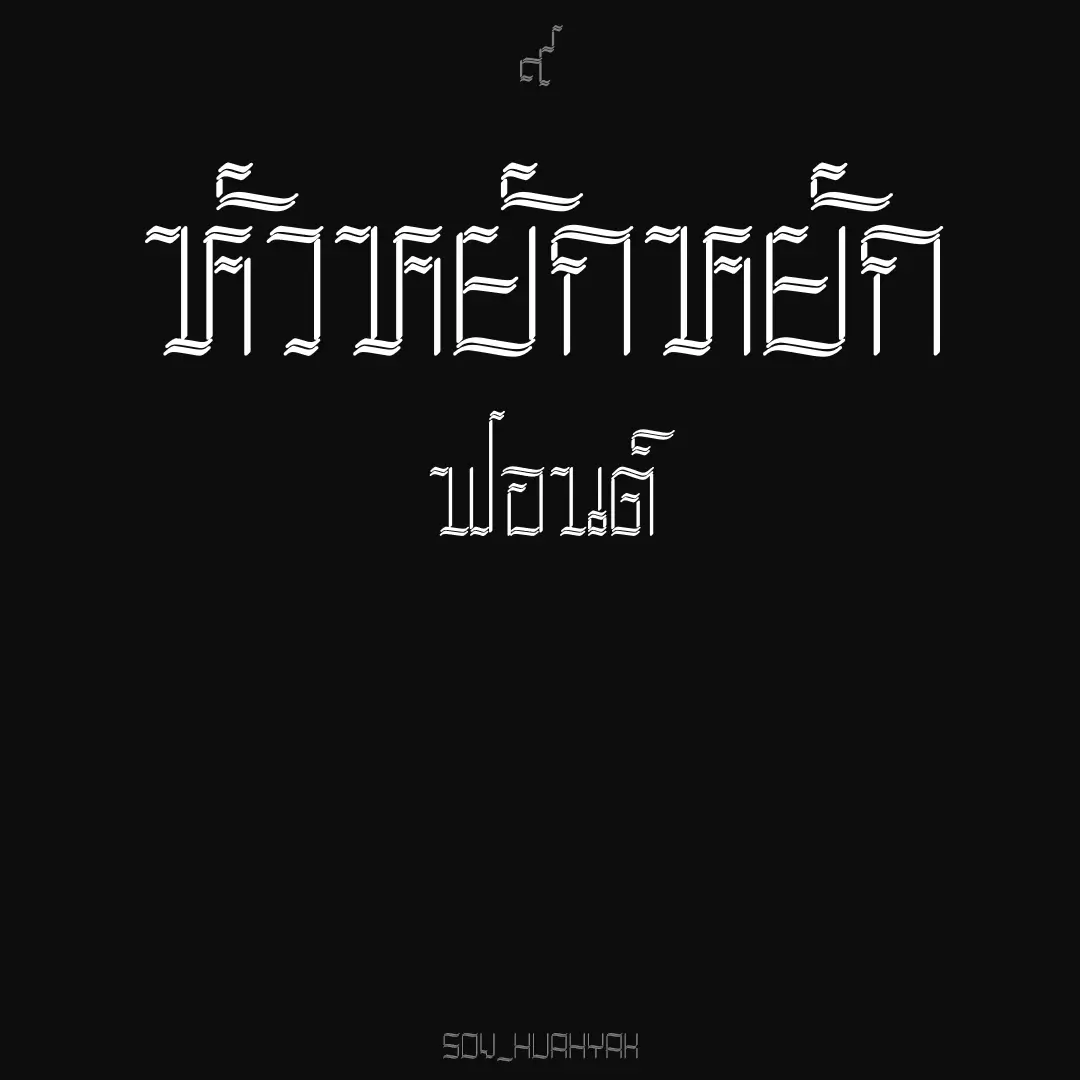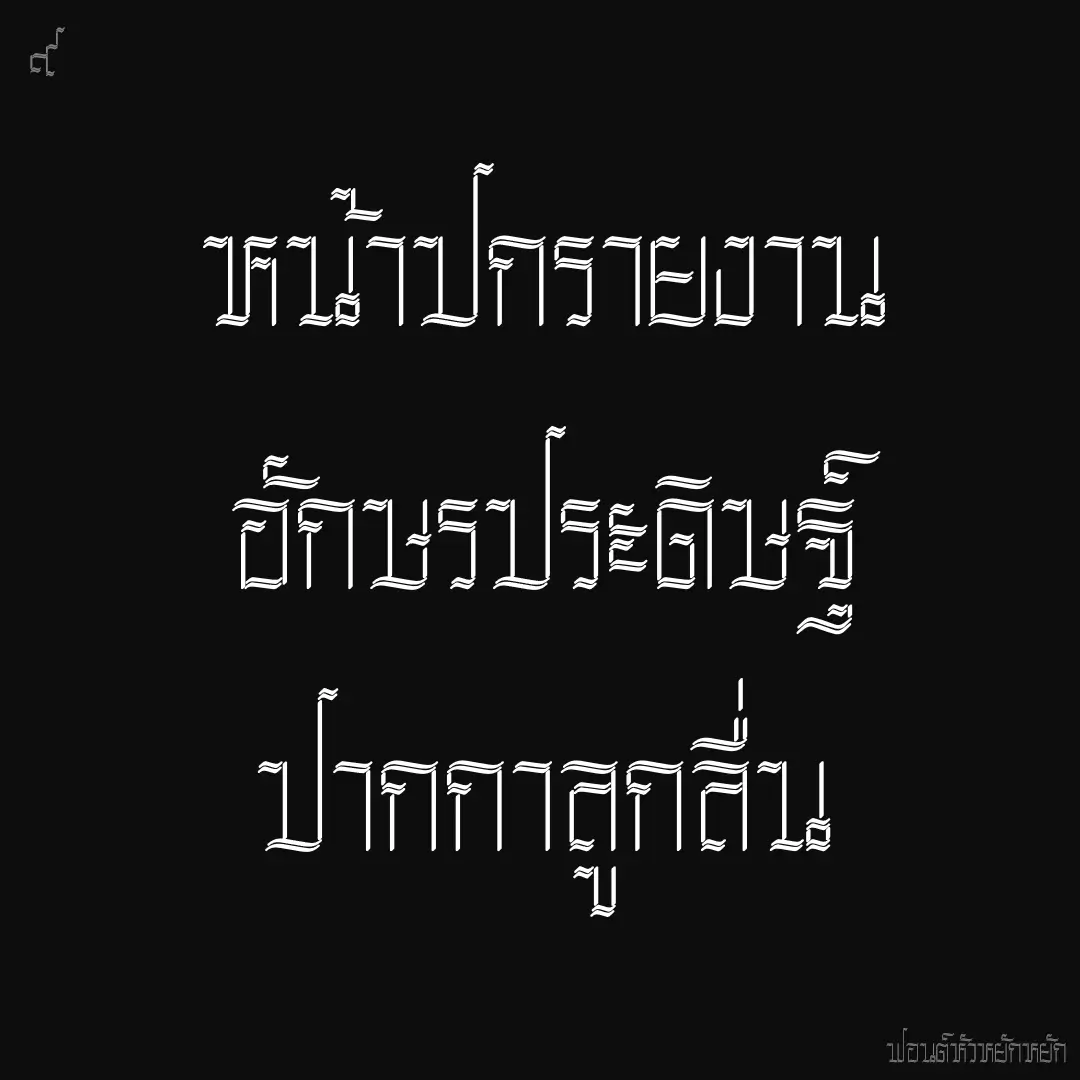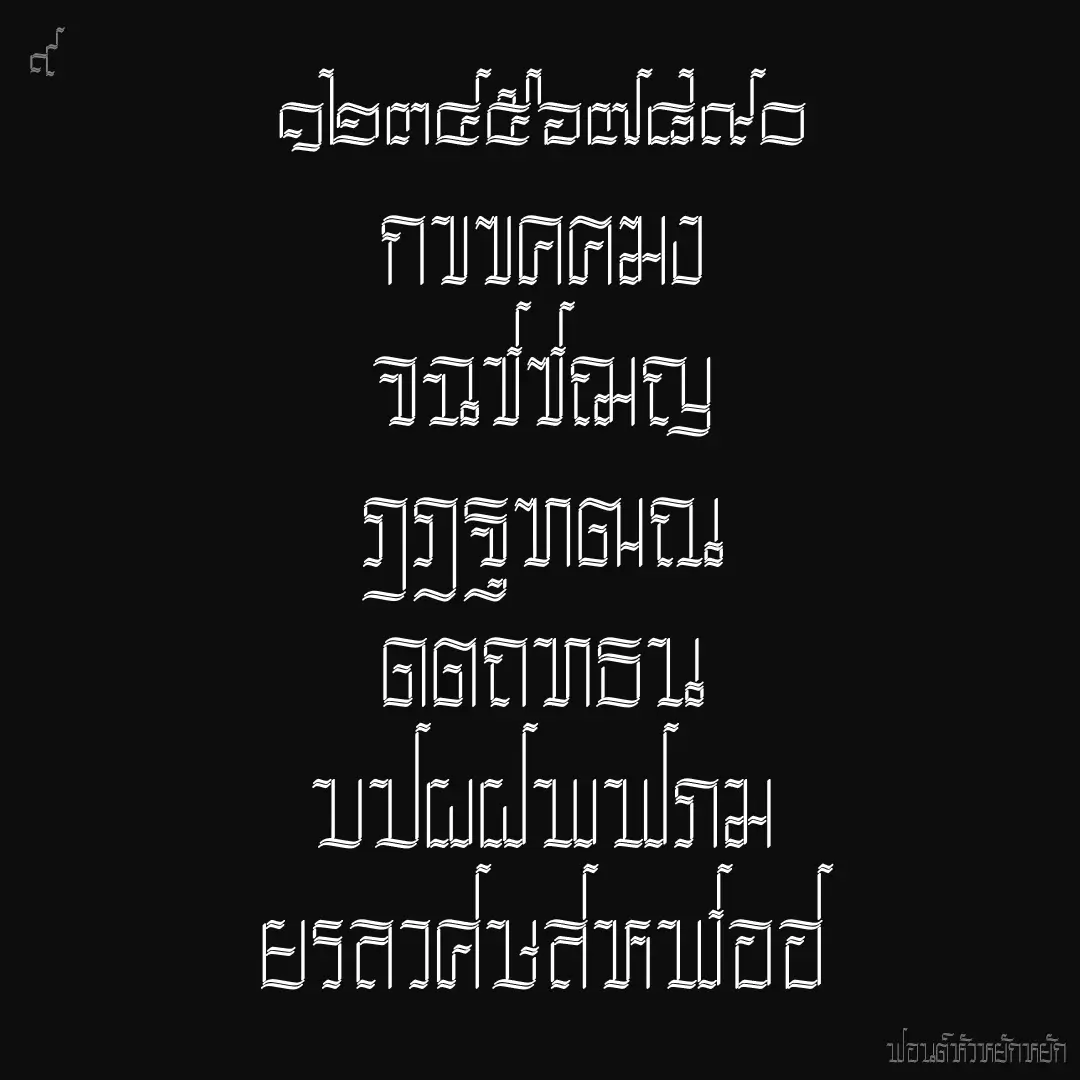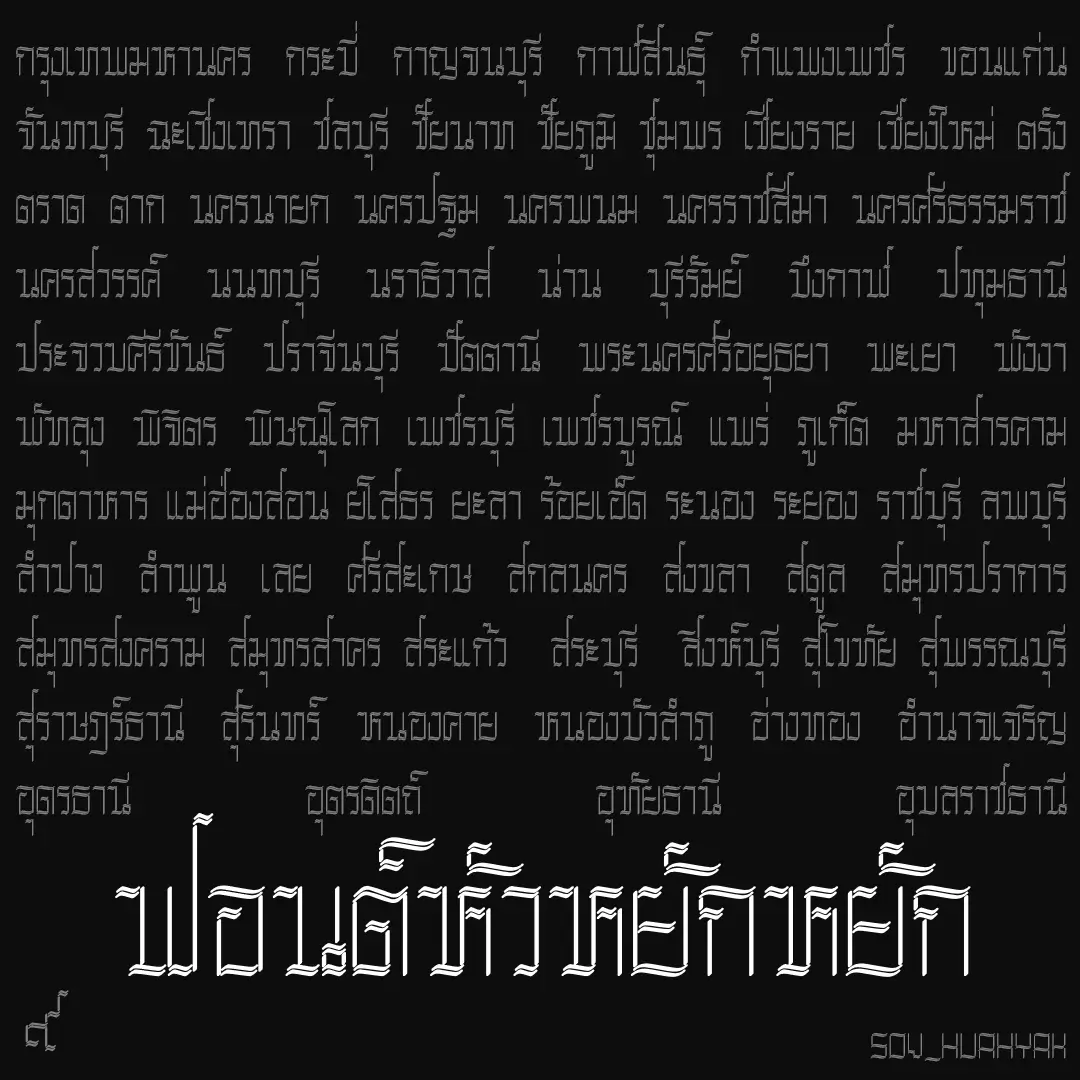
ฟอนต์หัวหยักหยัก – ฟอนต์หยักๆ เงาลางๆ จากลายมืออักษรประดิษฐ์ที่มักใช้เขียนปกรายงานสมัยเด็ก เนื่องจากลายมือปกติไม่สวย เอาปกสวยไว้ก่อน (สวยได้แค่นี้แหละ) พอคุณครูเปิดเข้าไปอ่านรายงาน แทบปาสมุดทิ้ง เพราะกระดาษฟุลสแก๊ปเต็มไปด้วยไก่เขี่ย (ไม่ตรงปก… มีมาแต่สมัยนู้นนนน)
เบื้องหลังการออกแบบ : ฟอนต์ หัวหยักหยัก
หัวหยักหยัก (SOV_HuaHyak)